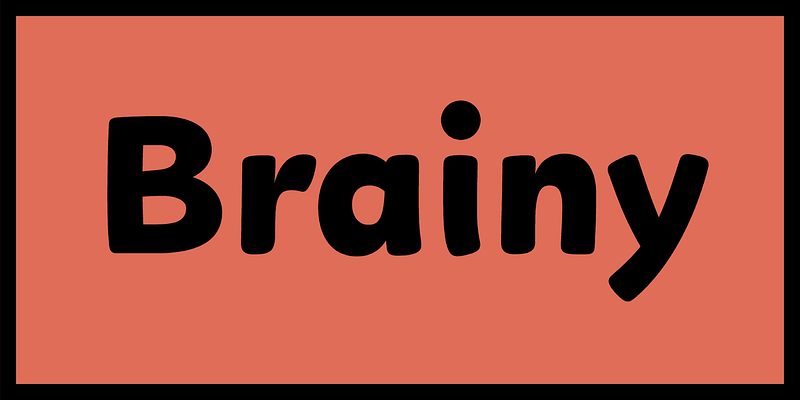
Fillip es una familia tipográfica para la lectura lenta. Ayuda a aprender a leer imitando el movimiento de la escritura y es algo imperfecta sin ser cómica. No contiene ligaduras y ofrece mucho espacio, una puntuación bastante grande y signos diacríticos marcados. En líneas generales, es amable, acogedora y legible. Fillip es una familia de fuentes fácil de utilizar con 4 grosores, desde ligero hasta negrita e incluso cursiva auténtica.